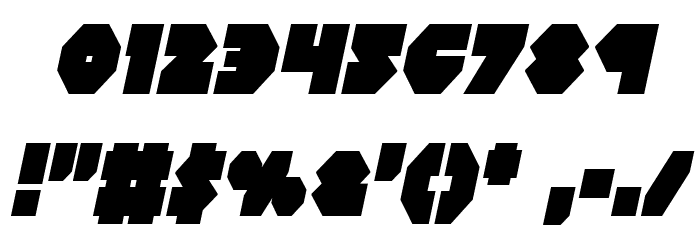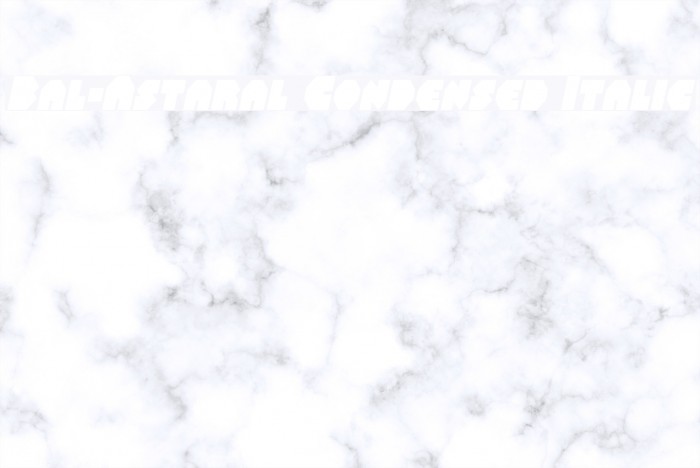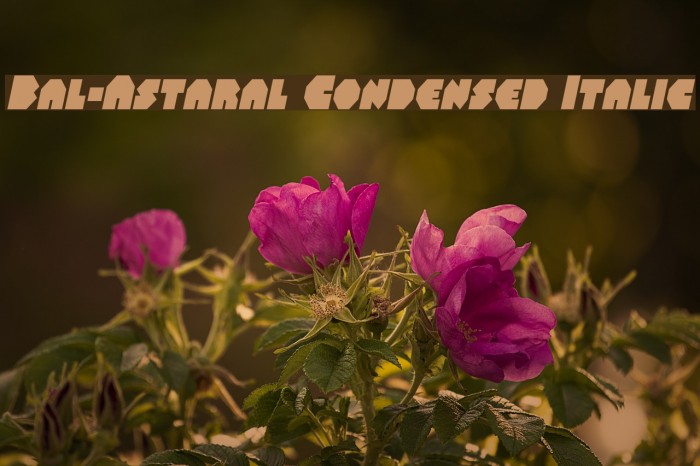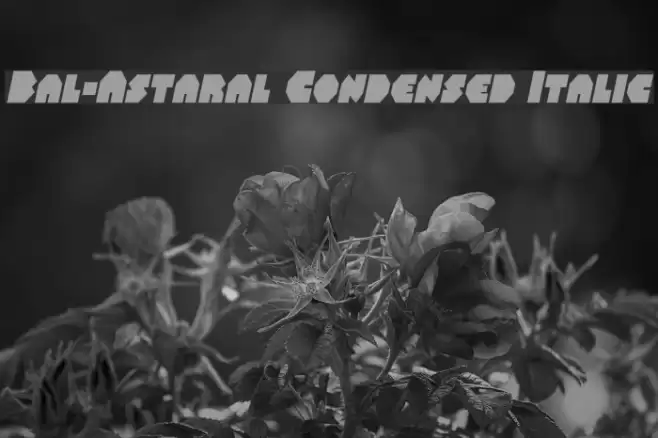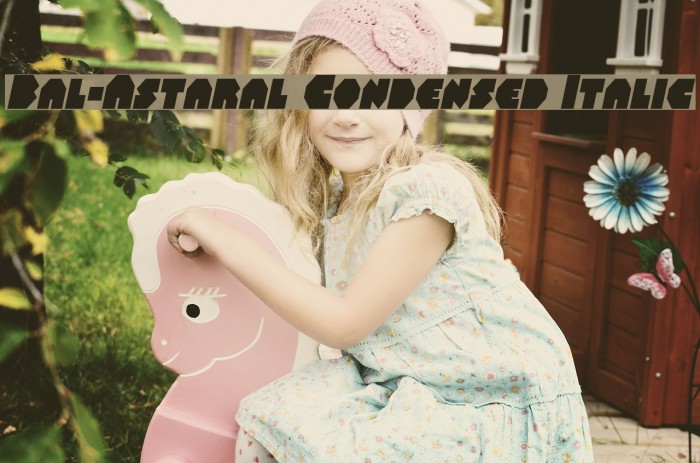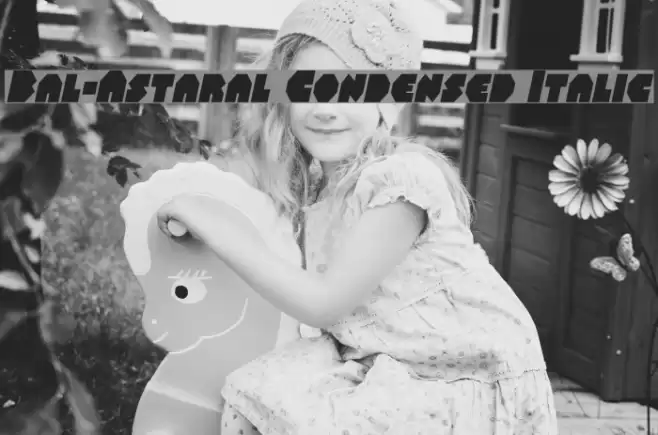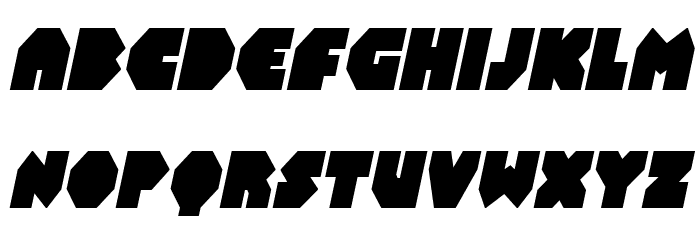
Bal-Astaral Condensed Italic Font
| Категория | Futuristic |
| Общий стиль | Futuristic |
| Область применения | Logos, Headlines, Posters |
| Рекомендуемые проекты | Ideal for sci-fi themed projects, modern branding, eye-catching posters, and innovative product packaging. |